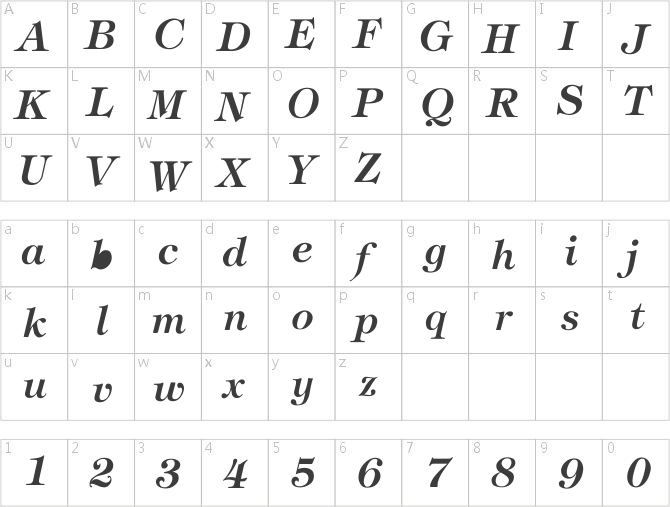
字体名称: Timpani
Timpani-BoldItalic
Timpani-BoldItalic介绍
Timpani-BoldItalic字体字库是一款让人赏心悦目、百看不厌的英文字体,适合各类广告和产品包装设计应用,字体大小0.06MB,格式为ttf字体,上传用户是afig,作者/版权方为未知
Timpani-BoldItalic效果图